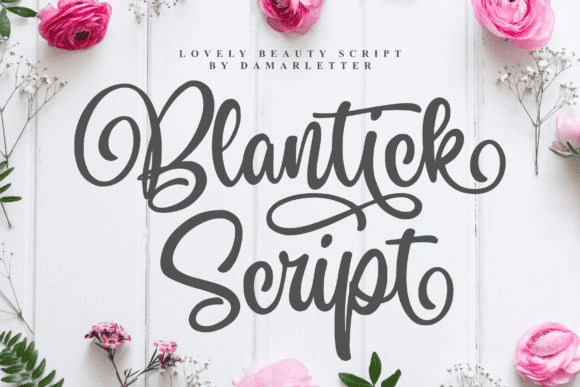
Название: Blantick Font
Blantick Script - это милый и дружелюбный рукописный шрифт.
Его естественный и неповторимый стиль делает его невероятно подходящим для большого количества рисунков.
Единственный предел - ваше воображение!